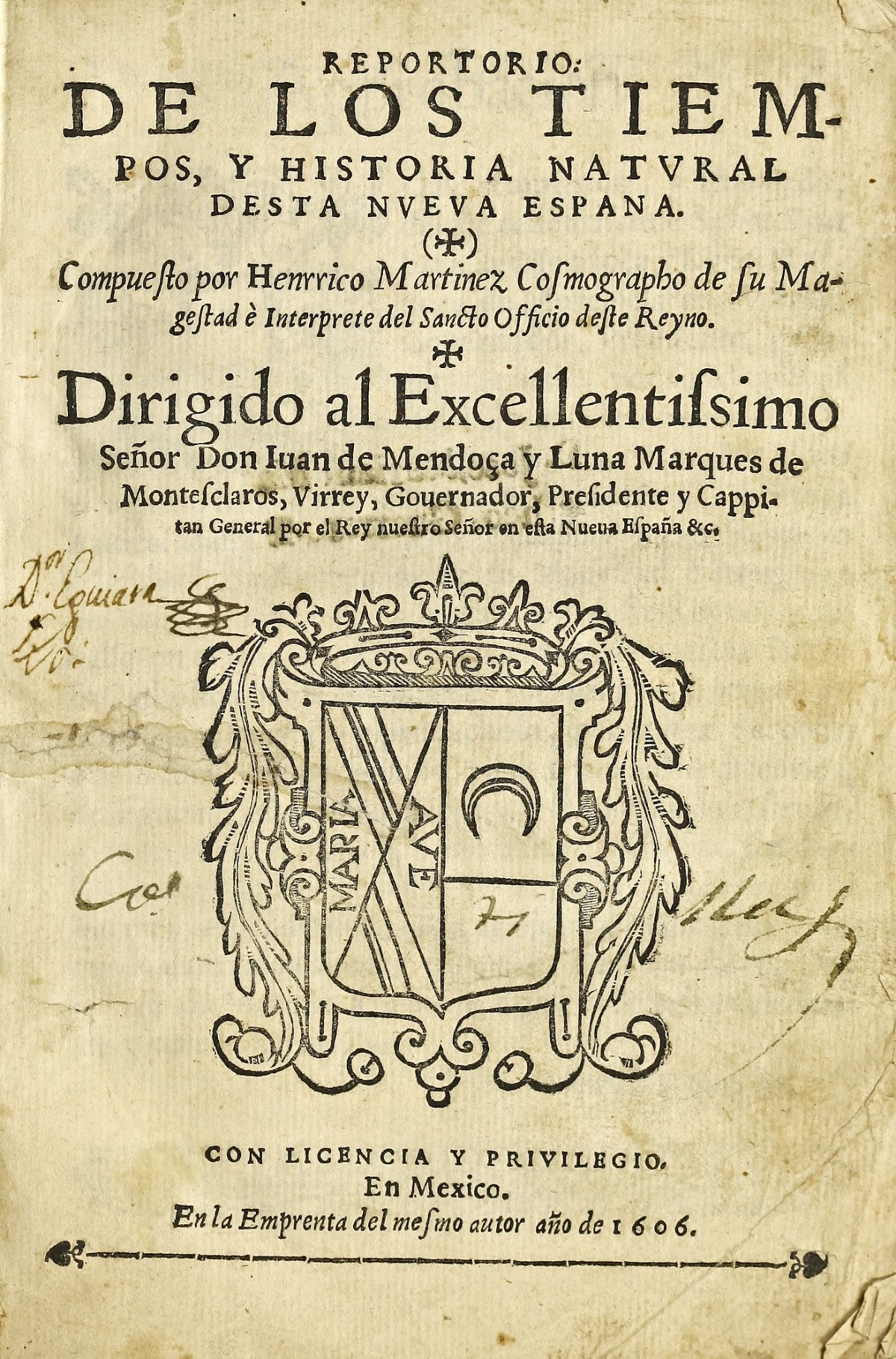
La consolidación de la tipografía latinoamericana
La tipografía latinoamericana tuvo su origen con los primeros impresores llegados a la Nueva España para cubrir la demanda de la producción de textos. El primero fue el sevillano Antonio de Espinosa (imagen 69), y es considerado el primer tipógrafo novohispano que incursionó en esta latitud en el tallado de letra entre 1554 y 1559 (Henestrosa: 2008, 61-65). También hay noticia de un empleado de Pedro Ocharte (imagen 70), de origen francés y llamado Juan Ortiz, quien por algunos documentos se sabe que fue fundidor de tipos y cortador de grabados en esta imprenta hacia 1560. (Griffin: s/f).
Otro no menos importante fue el alemán Henrich Martin (Enrico Martínez, imagen 71) llegado en 1589 y designado cosmógrafo real y que también talló varias fuentes (Segovia: 2001, 65-77). No es de extrañarse que no se supiera de más abridores de punzones en la Nueva España —sino hasta el siglo XVIII—, ya que el material y los insumos estaban regidos por la Corona española y los monopolios de comercio europeos. Sin embargo, en el primer cuarto del siglo XX, el pintor y grabador Francisco Díaz de León fundó en México el Instituto tipográfico.
Hacia fines del siglo XX, la creciente necesidad de investigar, teorizar y consolidar la disciplina fue la base de una corriente académica que buscó formar profesionales expertos en el tema: la introducción de programas de profesionalización como el ANRT, Atelier National de Recherche Typographique (1985), priumero en París y más tarde en Nancy, de la mano del ministerio de cultura francés; el Master Type and Media de la Real Academia de Artes de La Haya (1996); el MA en Typeface Design de la Universidad de Reading (1999), Reino Unido; o la introducción del Máster en Tipografía Avanzada del Centre Universitari de Disseny i Art de Barcelona (2003). Por otra parte en América Latina la apertura del Diplomado en Tipografía del Departamento de Estudios Tipográficos de la Universidad Católica en Santiago de Chile (2003), la Maestría en Diseño Tipográfico del Centro de Estudios Gestalt para el Diseño, en el puerto de Veracruz, México (2006), y la Carrera de Especialización en Diseño de Tipografía y más tarde Maestría en Tipografía de la Universidad de Buenos Aires (2008); permitieron el acceso al oficio en Latinoamérica y también contribuyeron a la participación de los latinoamericanos en el mercado internacional con propuestas innovadoras y en general con un estilo singular.
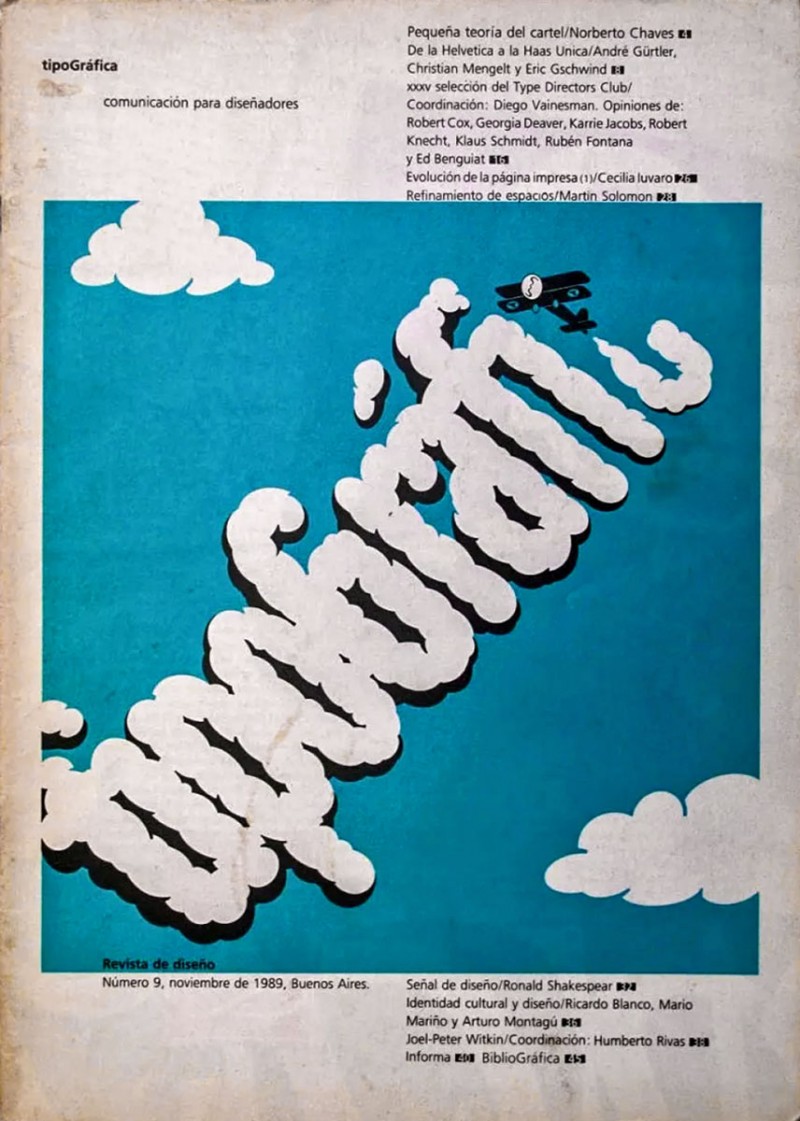
La tipografía latinoamericana inició ese proceso de consolidación en 1985 con el lanzamiento de la revista especializada TipoGráfica. Comunicación para diseñadores (imagen 72), dirigida por Rubén Fontana, quien influyó en muchas generaciones de diseñadores al abordar el tema desde un punto de vista más sustentado en la reflexión.
Desde un inicio la tipografía digitial latina evolucionó de forma diferente en dos latitudes: Centro y Sur. En la segunda, y evidentemente con mayor experiencia, destacaron diseñadores como Alejandro Paul (imagen 73), Alejandro Lo Celso (imagen 74), Francisco Gálvez (imagen 75), César Puertas, José Scaglione, Eduardo Manso y Eduardo Tunni (imagen 76), en cuyas manos el diseño de letra se renovó y adquirió un carácter único. Algunos de ellos han procurado la enseñanza de la tipografía en diversas latitudes y espacios académicos, además de escribir artículos sobre el tema. Al igual que en el resto del mundo suelen definirse dos perfiles más o menos claros: diseñadores de cierta versatilidad que abordan diversidad de proyectos, para texto o para rótulos, y diseñadores que se enfocan casi enteramente en un sólo género, como las fuentes script o las sanserif geométricas, géneros que suelen moverse más comercialmente.
Asimismo en Brasil, Chile, Colombia, Uruguay y Venezuela han destacado diseñadores como Gustavo Soares, Fernando Mello (imagen 77), Joaquín Contreras, Óscar Guerrero Canizares (imagen 78), Pablo René Marchant, José de los Santos, Javier Quintana (imagen 79), quienes han contribuido a la consolidación del estilo latinoamericano, y cuyo impacto y originalidad en las propuestas tipográficas han encontrado un nuevo nicho dentro del diseño europeo y estadounidense.
También, es importante mencionar que en esta latitud han colaborado tipógrafos europeos, como la checa Veronika Burian (imagen 80), o los españoles Laura Meseguer (imagen 81), Andreu Balius (imagen 82) y Jordi Embodas (imagen 83), quienes de un modo u otro también han influido y han recibido influencia de las propuestas tipográficas latinoamericanas.
En el Centro, y en específico en México, el diseño tipográfico floreció por un lado gracias a la influencia de la escuela sudamericana, y por otro a la incursión en la letra de talentosos autodidactas como Gabriel Martínez Meave (imagen 84), Quique Ollervides y Elí Castellanos (imagen 85) quienes imprimieron un estilo «nacionalista» inspirado en la cultura prehispánica o popular, y cuyos especímenes destacaron por su originalidad. Esta inquietud sobre la novel propuesta mexicana consolidó un par de publicaciones que no sólo se interesaron en el tema sino que fueron impulsoras de estos nuevos estilos. Así en 1997 se publicó el primer número de la revista Matiz del diseño gráfico internacional (imagen 86) que empleaba fuentes mexicanas tanto parta portada como para componer algunos títulos en los interiores. Hacia 1998 salió a la luz la revista DX. Estudio y experimentación del diseño (imagen 87), que en su quinto número abordó a los pioneros mexicanos de la tipografía. A medidados de 2002, surgió la primera revista mexicana especializada: Tiypo. Revista de tipografía (imagen 88). Para 2007, se editó el primer número de la revista Quadra. Diseño y comunicación visual (imagen 89), editada por la Universidad de Guadalajara.
La publicación de estas revistas permitió el acercamiento al mundo del diseño de fuentes y la necesaria academización de la tipografía. Lo anterior dio cabida a la apertura de la primera especialidad en tipografía por la Universidad Intercontinental de la Ciudad de México, más tarde, ésta se convertiría en la Maestría en Diseño Tipográfico del Centro de Estudios Gestalt para el Diseño, en Veracruz, de la cual, emergieron nuevos talentos como Oscar Yáñez (imagen 90), David Kimura, Cristóbal Henestrosa (imagen 91), Raúl Plancarte (imagen 92), Iván Moreno, Manuel López o Jesús Barrientos (imagen 93), por mencionar algunos, y quienes actualmente han posicionado a la tipografía mexicana en un plano privilegiado y han destacado por sus propuestas objetivas sin perder el carácter latino, mismo que se aprecia en sus especímenes.
El lanzamiento de la Bienal de Tipografía Latinoamericana Letras Latinas fundada en Argentina en 2004, fue la primera en esta latitud que versó sobre el diseño de fuentes, la cual abrió las puertas a muchos creadores —autodidactas y, también, a aquellos que contaban con una formación académica en este arte— para publicar su trabajo. Este primer esfuerzo conjunto, liderado por Rubén Fontana y con el apoyo de un gran número de universidades latinoamericanas, sumó las fuerzas de localidades como Buenos Aires, San Pablo, Santiago de Chile y Veracruz, México. En 2008 Fontana soltó las riendas y el evento se convirtió en la Bienal de Tipografía Latinoamericana Tipos Latinos, cuando México retomó el esfuerzo encabezado por Francisco Calles Trejo con el apoyo de otras instituciones educativas.